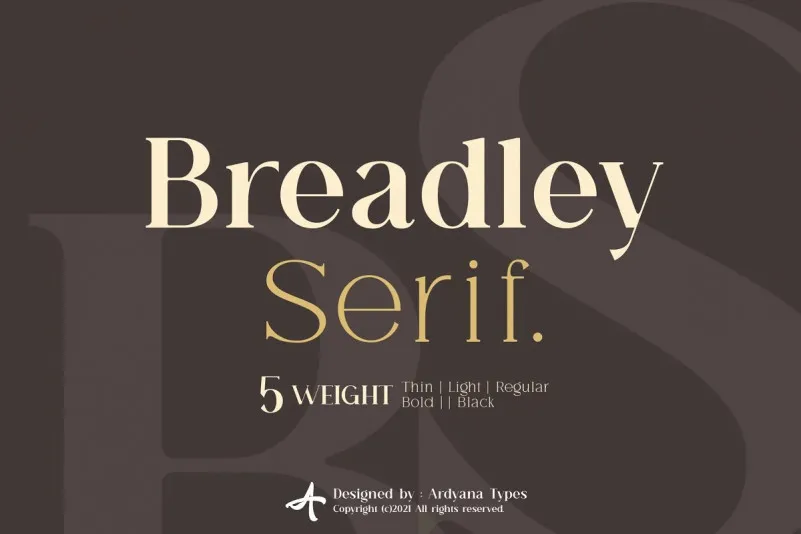
Breadley Serif Font – Download Grátis
Esta é uma elegante tipografia serif que surge naturalmente do famoso ‘Breadley Sans’ de Ardyanatypes. Construída para oferecer uma sequência suave e detalhada, a fonte ‘Breadley Serif Font’ mantém o estilo limpo e sofisticado dos seus antecessores enquanto adiciona pequenos elementos decorativos em alguns pontos finais das linhas que as tornam ainda mais expressivas. Perfeita tanto para títulos quanto para logotipos de marca, a fonte mantém um visual elegante e forte, capaz de destacar-se sozinha. É perfeitamente adequada para situações onde uma presença única e sofisticada é desejada. Engane-se se pensa que esteja apenas mais uma vez criando serifas – ‘Breadley Serif Font’ é um verdadeiro luxo visual, que transmite elegância sem comprometer a legibilidade.